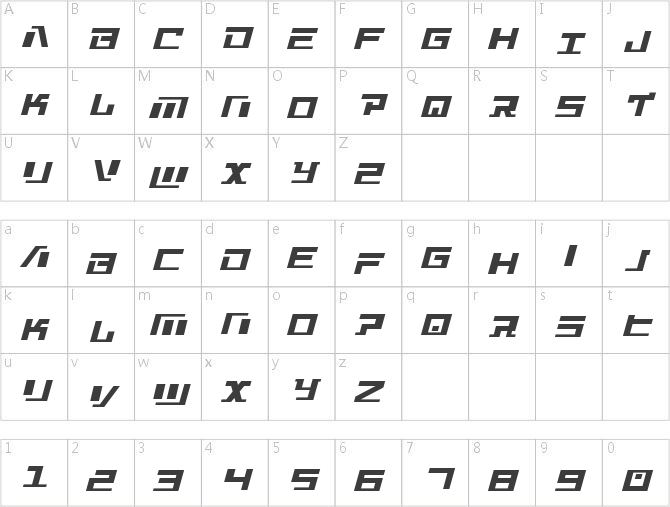
字體名稱: warmach
warmachinecond
warmachinecond字體字庫是一款讓人賞心悅目、百看不厭的英文字體,適合各類廣告和產(chǎn)品包裝設(shè)計(jì)應(yīng)用,字體大小0.02MB,格式為ttf字體,上傳用戶是dqq520,作者/版權(quán)方為未知